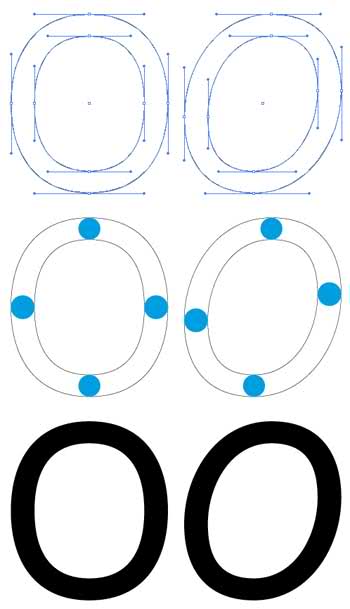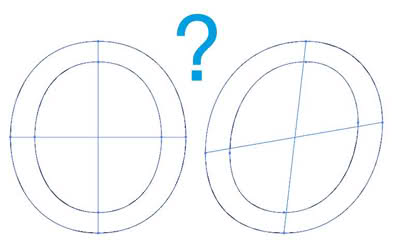
echte Kursiven erstellen
Ich beschäftige mich gerade damit eine Groteskschrift zu entwickeln, die ich in Illustrator zeichne und daraus in FontLab inportiere. Jede Type direkt in verschiedenen Stärken von "Thin" bis "Black".
Ich habe aber das Problem, dass ich nicht zurecht komme mit dem erstellen von kursiven Typen und euch mal fragen wollte ob Ihr eine möglichst unkomplizierte Methode kennt, wie man die erstellen kann. Die einfach zu rotieren und transformieren sieht ganz schlimm aus. Ich dachte mir, dass es möglich wäre das über steilere Achsen zu machen, aber das ist ewig aufwendig und erscheint mir auch sehr ungenau.
hilft dir das weiter?
Ansonsten gilt: die Tangenten sollten hier ausnahmsweise nicht an den mathematischen Extrempunkten (also ganz links und rechts außen und senkrecht) liegen, sondern zum einen dem Winkel der Kursive entsprechen und an den "optischen" Extrempunkten anliegen. Erst in der Produktion dann die Extrempunkte an den mathematischen Extremen ergänzen (vor allem wegen Hinting).
Ich habe gestern Abend noch ein wenig rumprobiert und bin zu einer Lösung gekommen, die der aus Deinem Link nicht unähnlich ist.
Ich habe die horizontale und vertikale Achse um einen festen Wert versetzt und die dabei gestauchten Kurven um einen weiteren festen Wert ausgeglichen. Das hat nach meinem Empfinden auch für alle Strichstärken gut funktioniert.